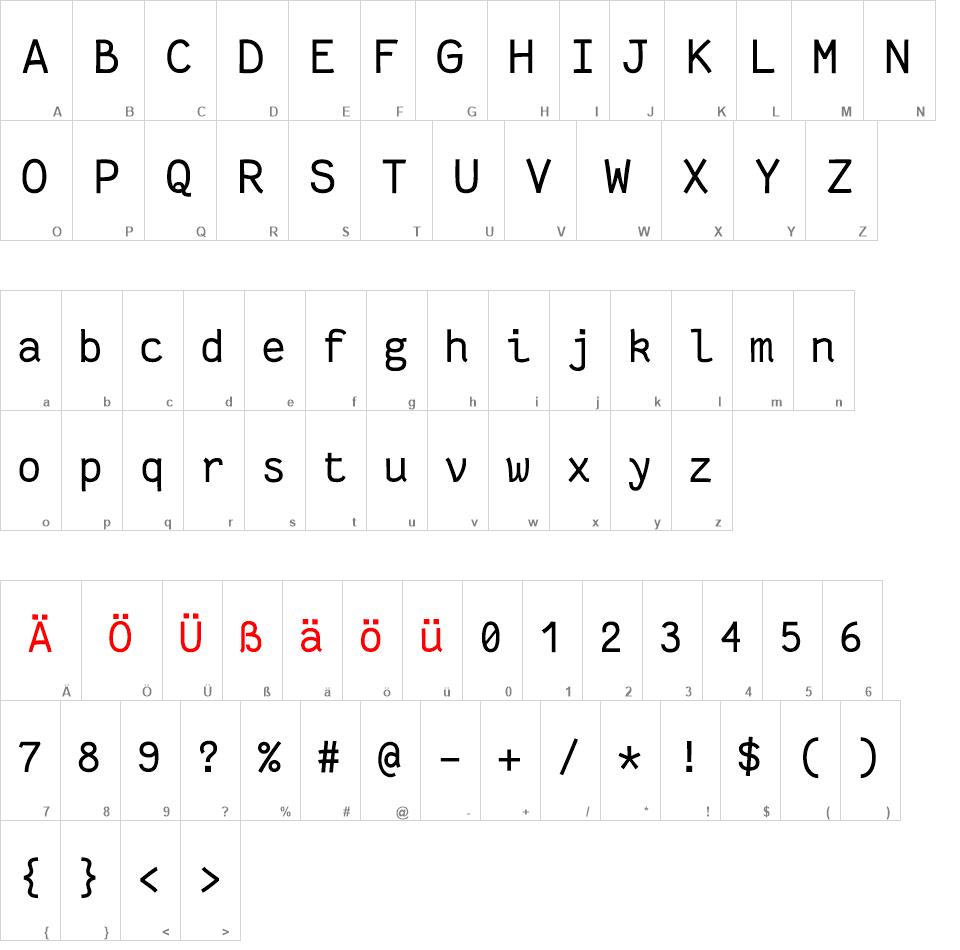
Fantasque-Sans-Mono
Eine Programmier-Schriftart, die auf Funktionalität ausgelegt ist und eine wabbelig-wackelige, handschriftliche Unschärfe aufweist, die sie unheimlich cool macht.
Früher bekannt als Cosmic Sans Neue Mono. Es stellte sich heraus, dass ähnliche Namen bereits für andere Schriftarten verwendet wurden, und dass Leute ihren instinktiven Hass auf Comic Sans auf genau diesen meiner Schriften ausweiteten (was natürlich nur geliebt werden kann). Warum der vorherige Name? Hier ist meine ursprüngliche Erklärung:
Der Name kommt von meiner Erkenntnis, dass es irgendwann wie das Mutantenkind von Comic Sans und Helvetica Neue aussah. Hoffentlich ist es nicht mehr der Fall.
Inspirierende Quellen sind Inconsolata und Monaco. Ich habe Consolas auch viel in meinem Programmierleben verwendet, daher mag es einige Gemeinsamkeiten haben.